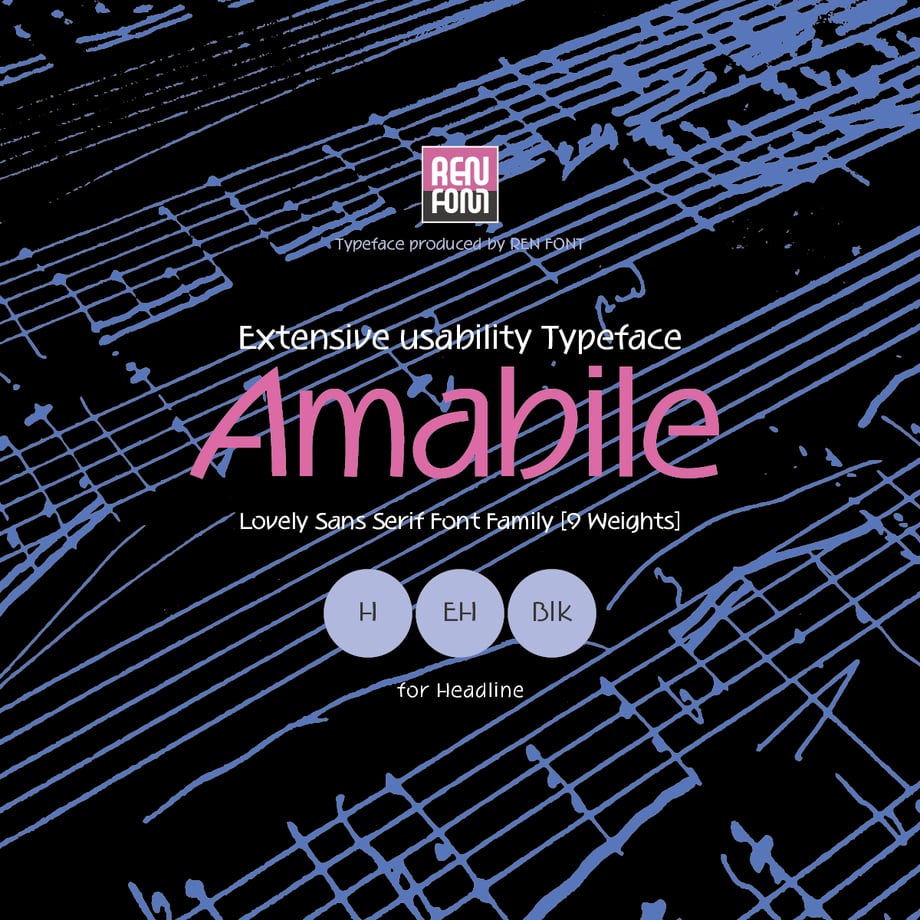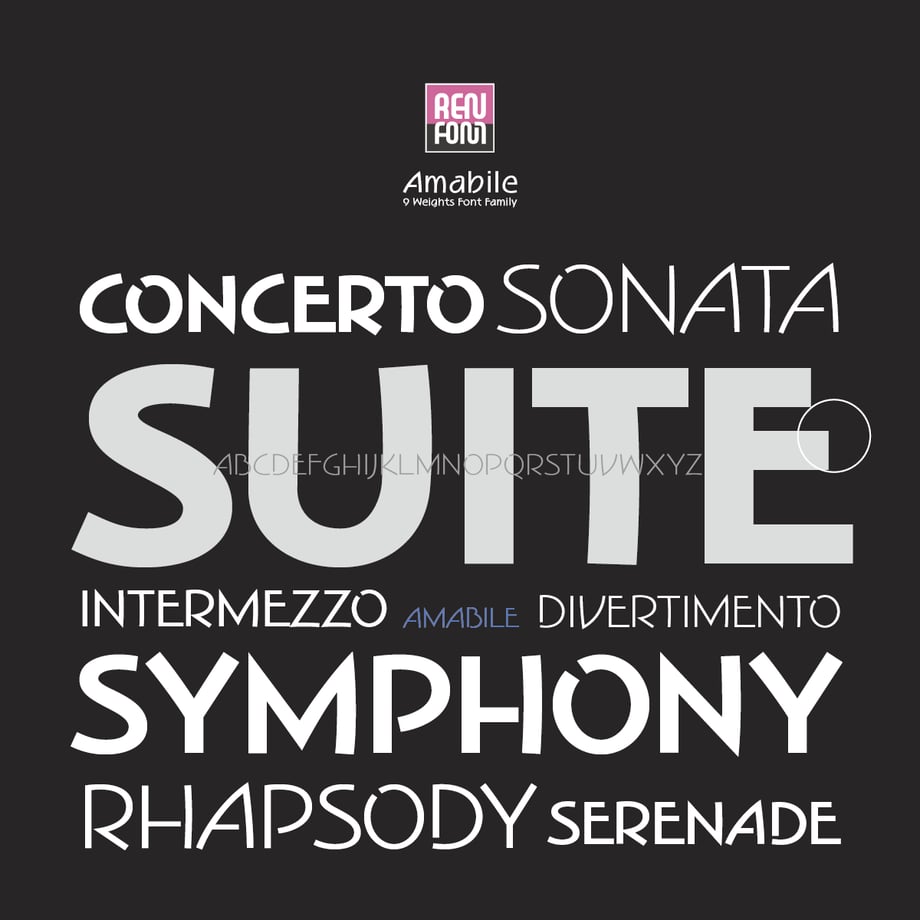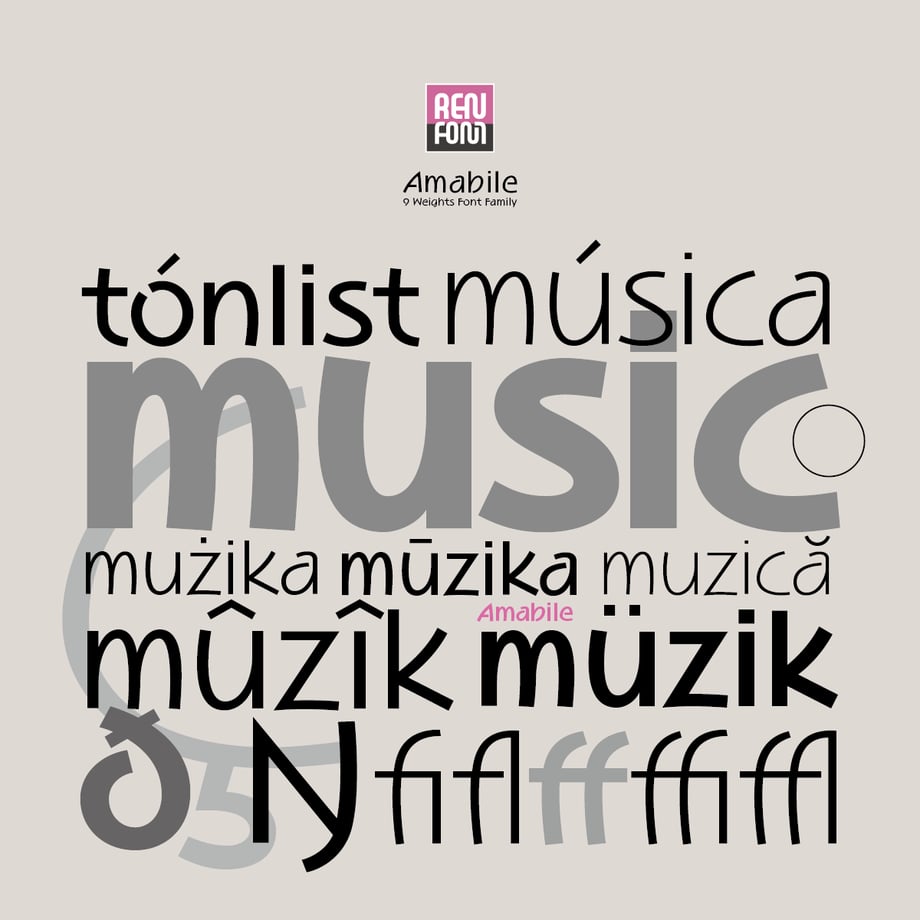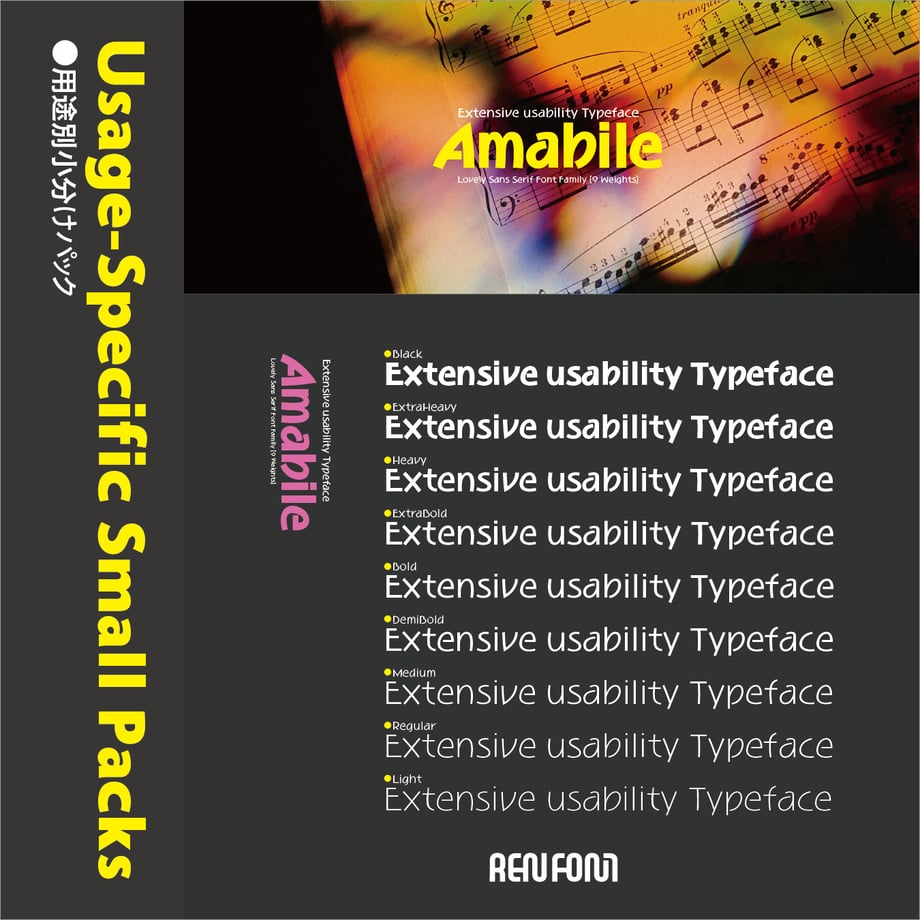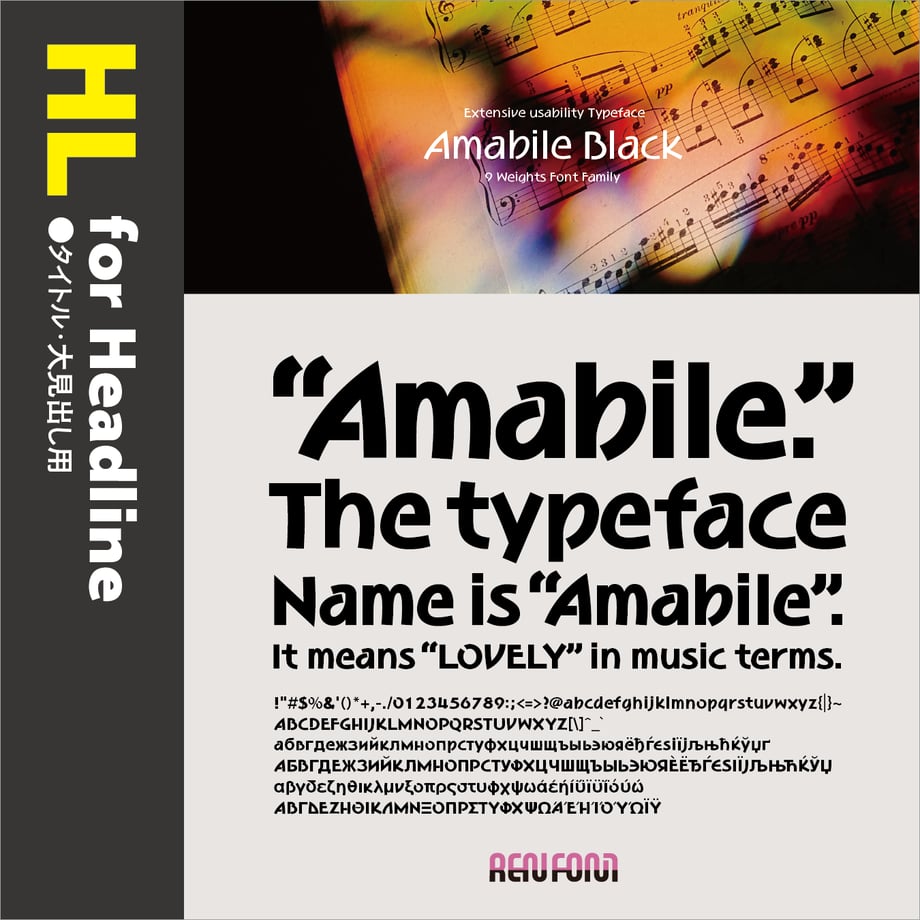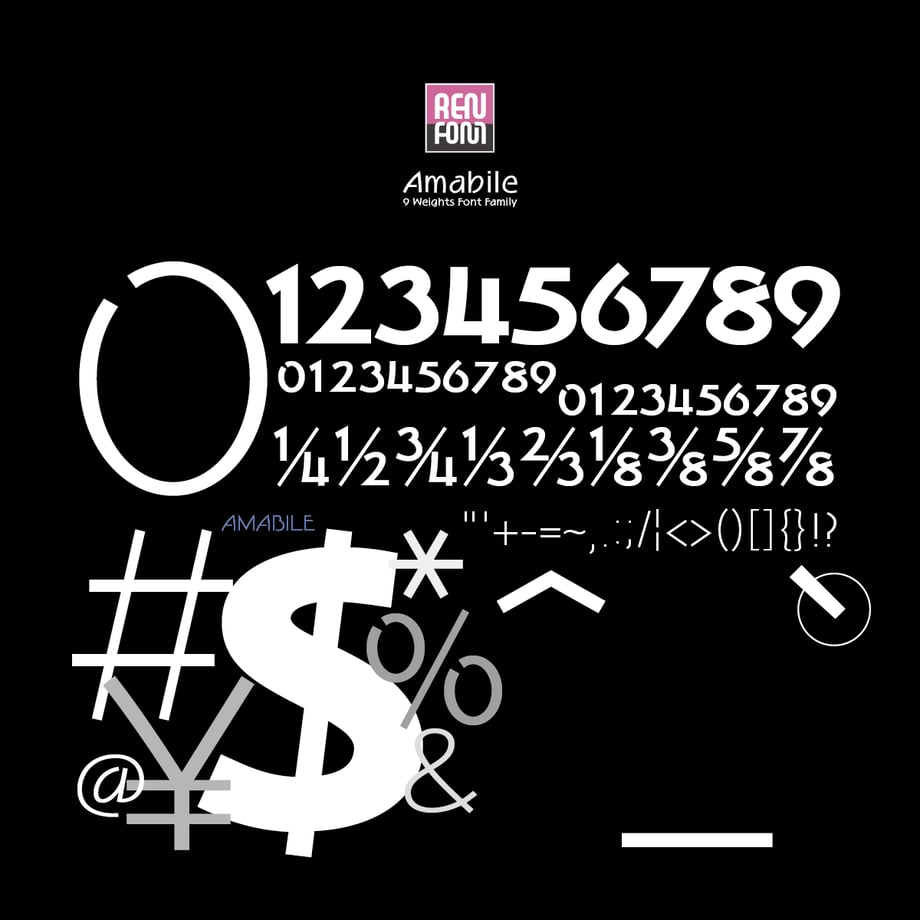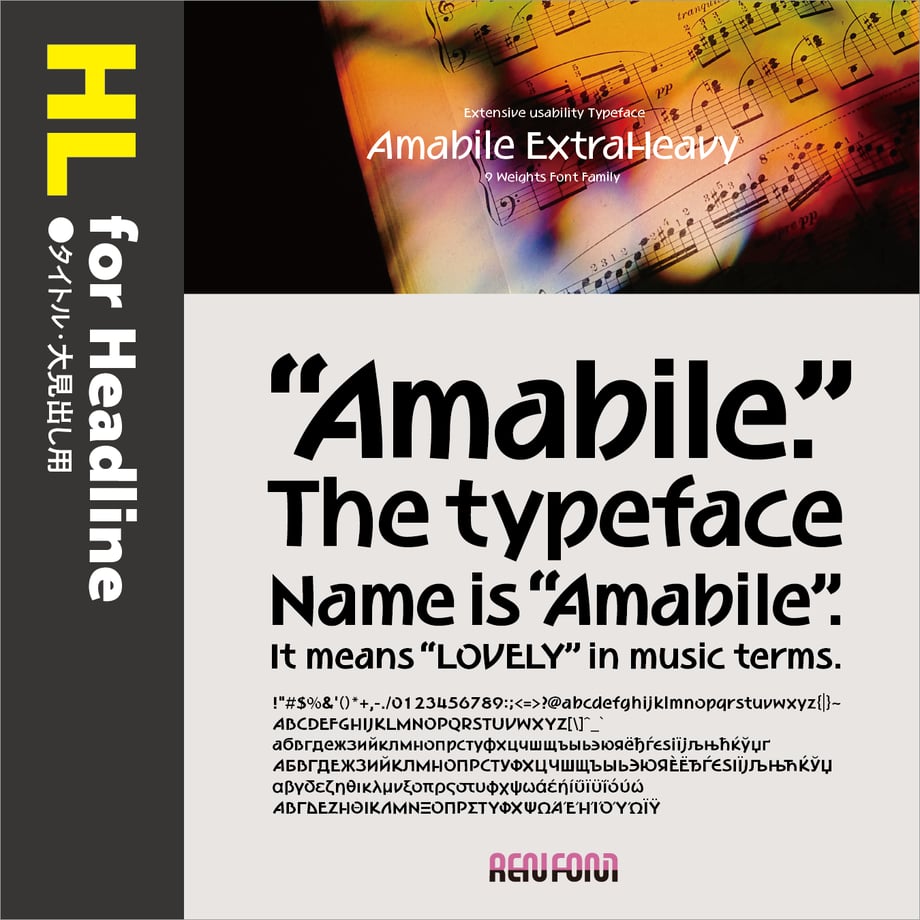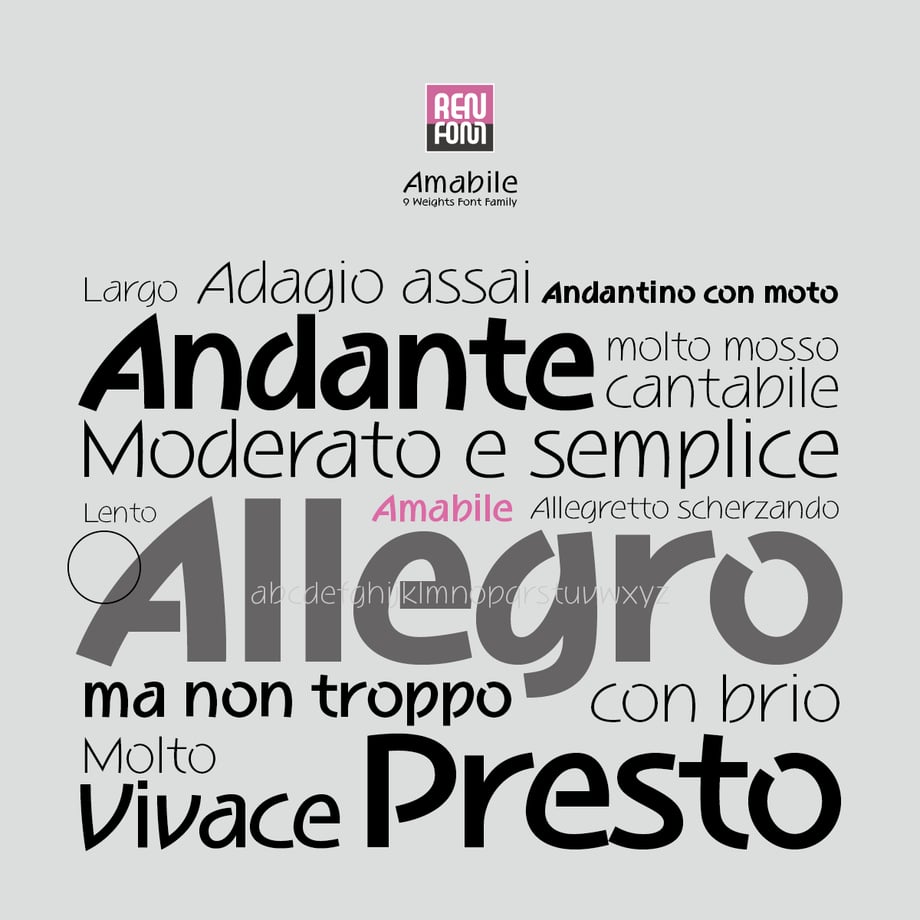
Amabile-HL(タイトル・大見出し用)H/EH/Blk
■About Amabile
The typeface name is "Amabile". It means "lovely" in music terms.
■Characteristics of Amabile
The design feature reflects the feature of Japanese typeface "Waon", as the depending latin characters of which this typeface is designed.
Motif of quarter note
"Amabile" briefly expresses the "basic concept of Waon, to express a music with typeface".
Firstly we started designing [d] and [p] for the basis of the feature of quarter note with slant oblong. Then we derived the form of other characters with this basic design. Latin characters, especially the lower case ones, have an arc for their basic form. We made the most of them and designed the plesurable mood with large counter.
Separating parts those properly are joined
Almost all of the characters in "Waon" have a feture that the part of the character is separated intentionally. "Amabile" have this feature too. This design feature produces an effect like a staccato in music note over the composition of letters.
Ending line with a gentle curve
Following the feature of "Waon", "Amabile" also have the feature that the stems and strokes in the ending line expresses the trajectory of the tact that the conductor swung down. This gentle curve is a feature not found in other typefaces, and mellowness is added to letters, and when assembled, unique lightness like operetta is born.
Tall X-height
The sans serif typeface is generally designed with a tall X-height. As a result, one letter is bigger and the contemporary atmosphere becomes stronger than the serif typeface.
"Amabile" further raises the X-height, there is not much difference between uppercase and lowercase letters. By designing a lowercase arc a little more strongly, we express fun and loveliness.
Uppercase letters those dare to break theory
We dare to sway the centeroid of the upper case characters. For example "A". We shifted the position of the apex (top pointed tip) to the right greatly. At first glance this design feature leads to misunderstand that the character is italic form. We made the biggest adventure with the first letter.
In addition to that, we set the position of the center of gravity of the character with the two-story structure to the opposite position ("H", "K", "P", "R, "X", "Y"), or the upper and lower contrast to the extreme ("B", "E", "F", "G", "S") so that we can make a bigger rhythm.
More character types
The non-Japanese characters in the Japanese font are basically composed with Latin, Cyrillic, and Greek. In addition to these 3 types of characters, "Amabile" have the capability of 87 languages by extending character types so called "W1G", which consists of Latin supplements, Cyrillic supplements, Greek supplements, Latin extensions.
■Amabile について
書体名は「Amabile(アマービレ)」。音楽用語で「愛らしく」という意味があります。
■Amabile の特長
「和音」の従属欧文として制作された性格上、当然ながら「和音」の特長を反映したデザインになっています。
四分音符をモチーフ
「和音」の基本コンセプトである「文字で音楽を表現する」を、最も端的に文字通り「表現」しているのがこの「Amabile」です。
楕円形を斜めに配した四分音符をイメージし、最初に小文字の [d] [p] を基本形としてデザイン。これをもとに他の文字種のフォルムを派生させていきました。欧文の、特に小文字は円弧が基本形にあるため、それを最大限に活かし、ふところの深い楽しい雰囲気の文字に仕上げました。
本来交わる部分を離す
「和音」はほとんどすべての文字のどこか1か所が切れて離れたデザインになっています。したがって、「Amabile」もそれを踏襲しています。この措置が、組んだときにスタッカートのようなアクセント豊かな効果を生んでいきます。
ゆるやかなカーブを描く収筆
これも「和音」の特長を踏襲しています。収筆(筆順の最後)のステム(縦画)、ストローク(斜画)に、指揮者が振り下ろすタクトの軌跡を表現しました。このゆるやかなカーブは他の書体にない特徴で、文字にまろやかさが加わり、組んだときに、まるでオペレッタのような独特の軽やかさが生まれます。
背の高いエクスハイト
サンセリフ書体は、一般的にエクスハイトが高めにデザインされています。それにより一文字ひともじが大きめになり、セリフ書体と比べて、現代的な雰囲気が強くなります。
「Amabile」は、さらにエクスハイトを高めにし、大文字と小文字の差があまりありません。小文字の円弧をより強めにデザインすることで、楽しさ愛らしさを表現しました。
あえてセオリーを崩した大文字
文字の重心をあえて崩した作りになっています。たとえば [A]。アぺクス(上部の尖がったところ)の位置を大幅に右にずらしました。一見すると「イタリック?」と勘違いします。最初の文字で最大の冒険をしました。
そのほかにも、上下2段の構造を持った文字の重心を、本来とは逆の位置 [H] [K] [P] [R] [X] [Y] 、もしくは上下のコントラストを極端 [B] [E] [F] [G] [S] にし、より大きなリズムを刻めるようにしました。
文字種をより充実
ほとんどの和文書体の従属欧文は Latin, Cyrillic, Greek の3種類が基本です。「Amabile」はこの3種類に Latin 補助、Cyrillic 補助、Greek 補助、Latin 拡張などを加えた、いわゆるW1Gの規格にプラスアルファし、87か国言語を表現できる多言語フォントに生まれ変わりました。
グリフ形状は、比較的自由にデザイン表現が可能な Latin 以外は「Amabile」の特徴を残しつつ、ネイティブの形状を壊さない、ぎりぎりの選択を施してあります。